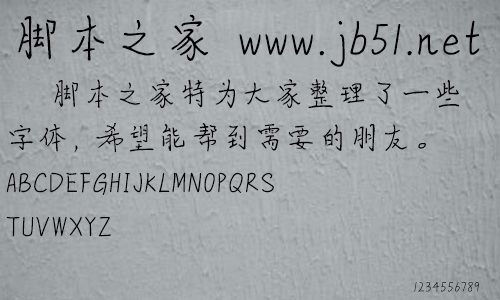
X-情感手跡由XFont字庫(kù)出品的藝術(shù)字體,字體筆觸較粗細(xì)適中,具有很好的視覺感,適合應(yīng)用于藝術(shù)設(shè)計(jì)、平面宣傳設(shè)計(jì)、網(wǎng)頁(yè)設(shè)計(jì),書法字帖等領(lǐng)域。有需要的朋友快來本站下載使用吧!